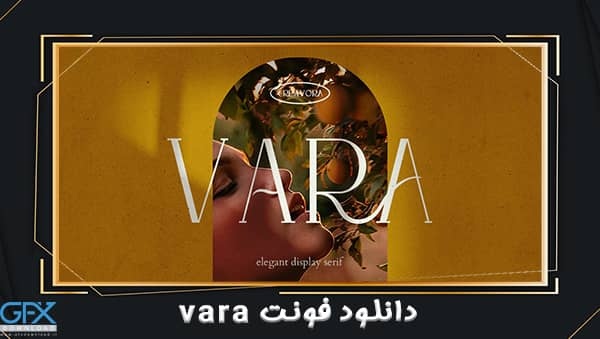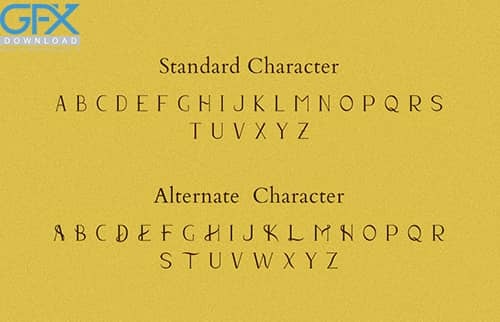
دانلود رایگان فونت Vara
دانلود رایگان فونت انگلیسی Vara
اگر به فونت خلاقانه و شیک برای طراحی خود نیاز دارید ، پیشنها ما به شما دانلود رایگان فونت Vara از جی اف ایکس دانلود است. یک فونت زیبا است که جلوه زیبایی بیشتری به پروژه بعدی شما می بخشد. به شما امکان می دهد لوگو تایپوگرافی را به سرعت و به آسانی انجام دهید. شما می توانید در طراحی های مختلف از این فونت انگلیسی زیبا استفاده نمایید.